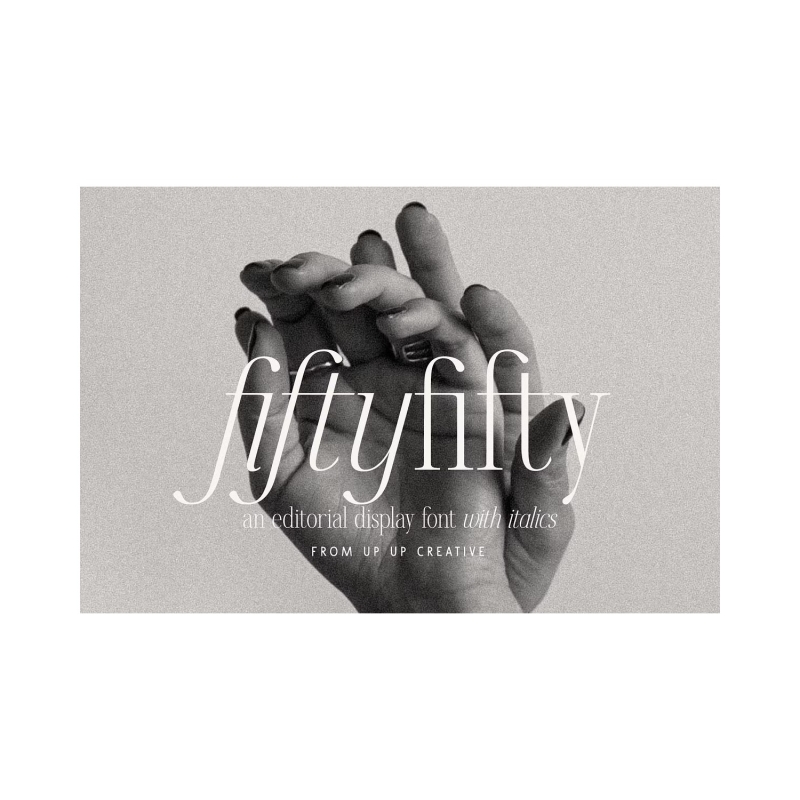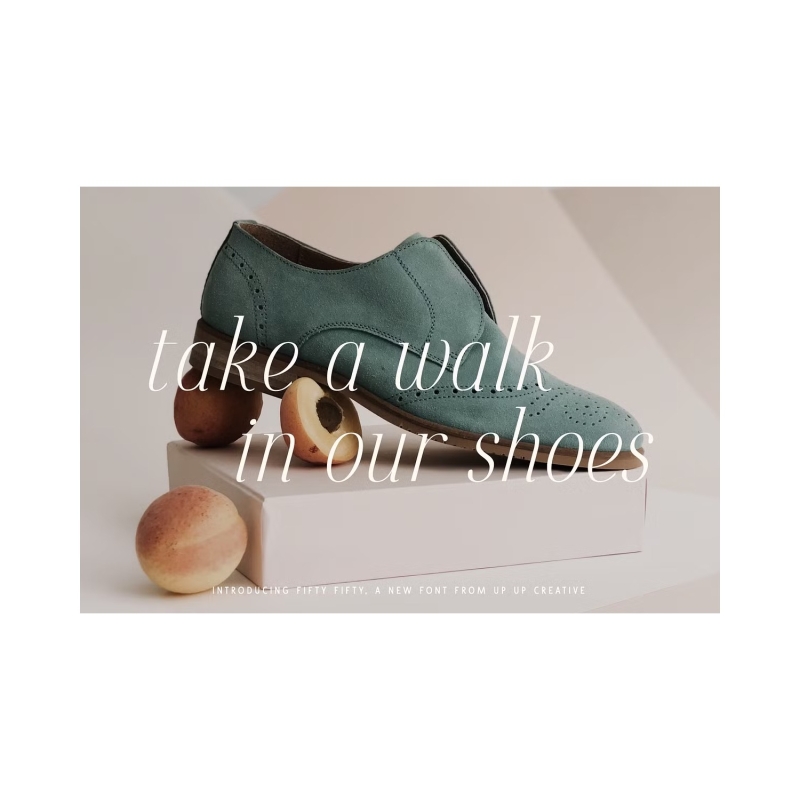
Fifty Fifty - Fuente serif con cursiva
Fifty Fifty es una fuente editorial serif (normal y cursiva) con curvas suaves y más de 100 ligaduras. Es precioso en mayúsculas, pero las letras minúsculas pueden valerse por sí solas. Fifty Fifty es perfecto para titulares, diseño editorial, monogramas, marcas, logotipos, diseño de carteles y más.
Fifty Fifty incluye aproximadamente 700 glifos y la friolera de 115 ligaduras estándar y discrecionales. Las características adicionales de OpenType incluyen variantes de caracteres, conjuntos estilísticos y soporte multilingüe (incluidos varios símbolos de moneda).